Сделайте текст красивым шрифтом с эффектом трещин. Идеально для элегантных и хрупких надписей.
Футуристичный красивый шрифт с переливающимися цветами. Для технологичных и геймерских надписей.
Сладкий и привлекательный дизайн для красивых надписей на тему еды, десертов и детских брендов.
Сочный 3D граффити шрифт для создания динамичных и молодежных красивых надписей.
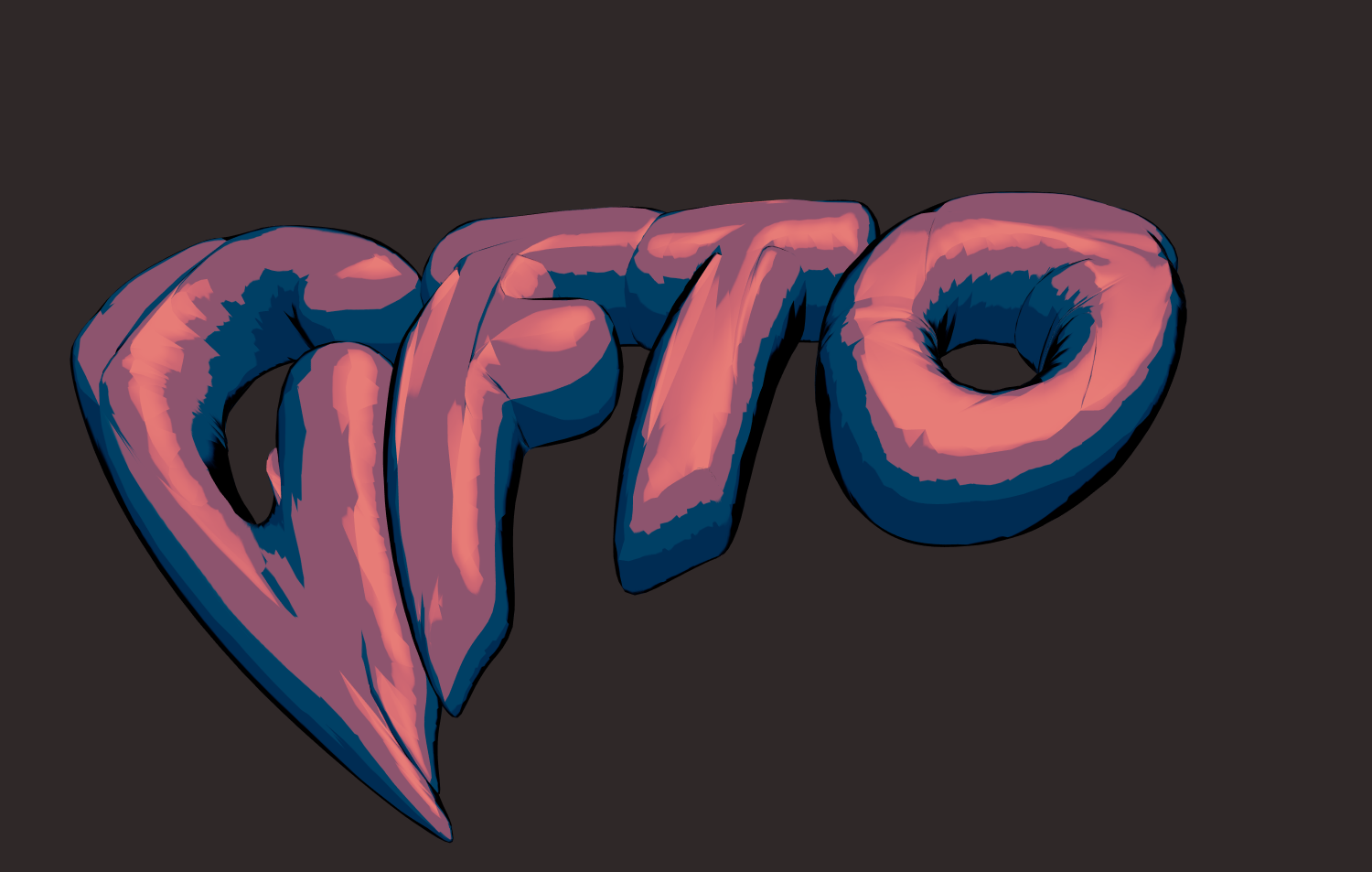
Мрачный и яркий стиль, чтобы сделать текст по-настоящему пугающим. Идеально для Хэллоуина и игр.
Сделайте надпись с реалистичным зеркальным отражением. Премиальный и технологичный вид.
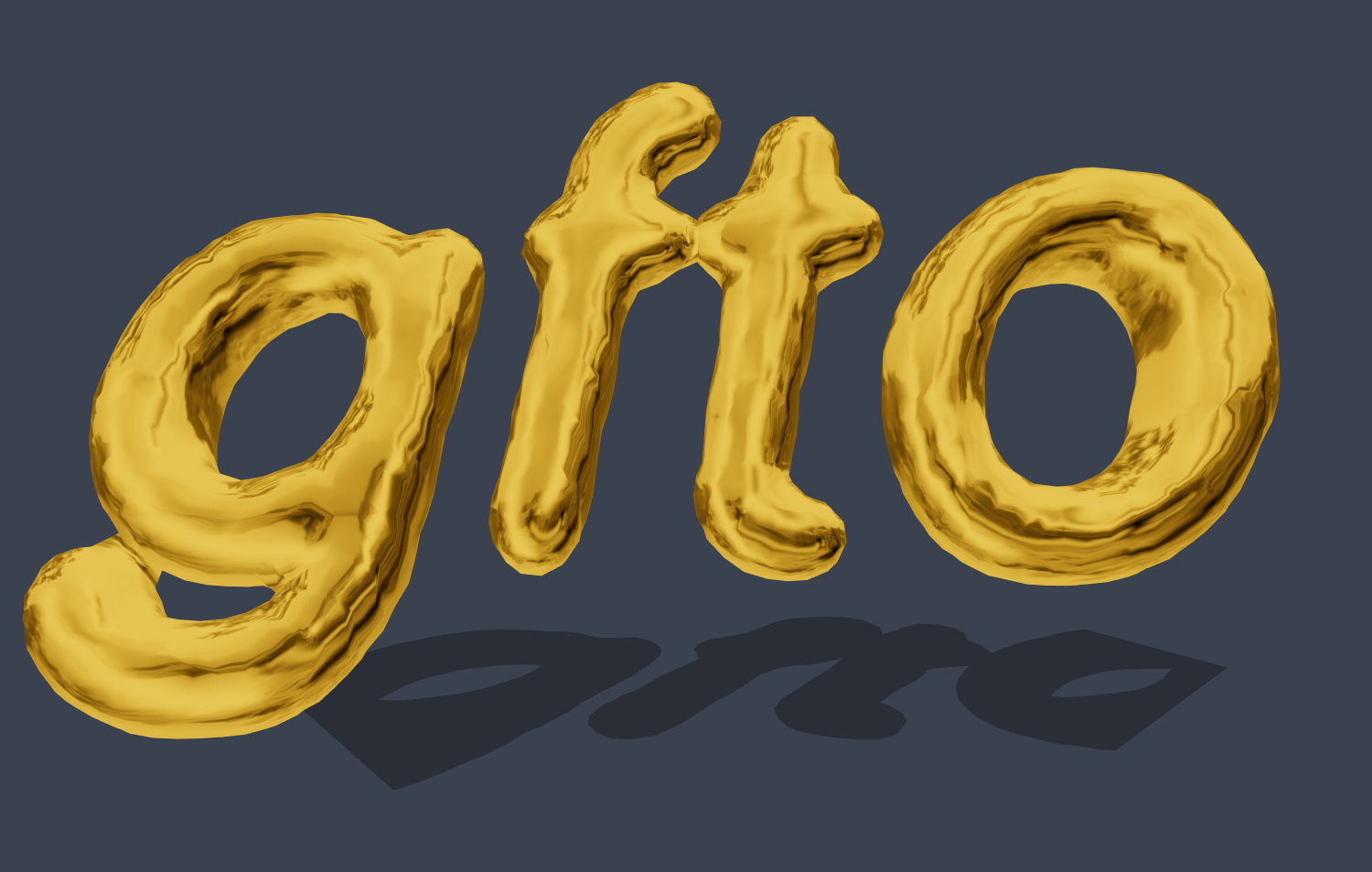
Объемные золотые буквы с глянцевой поверхностью для создания роскошной и красивой надписи.
3D эффект с органической формой. Плавные линии и реалистичная жидкая текстура для вашей надписи.
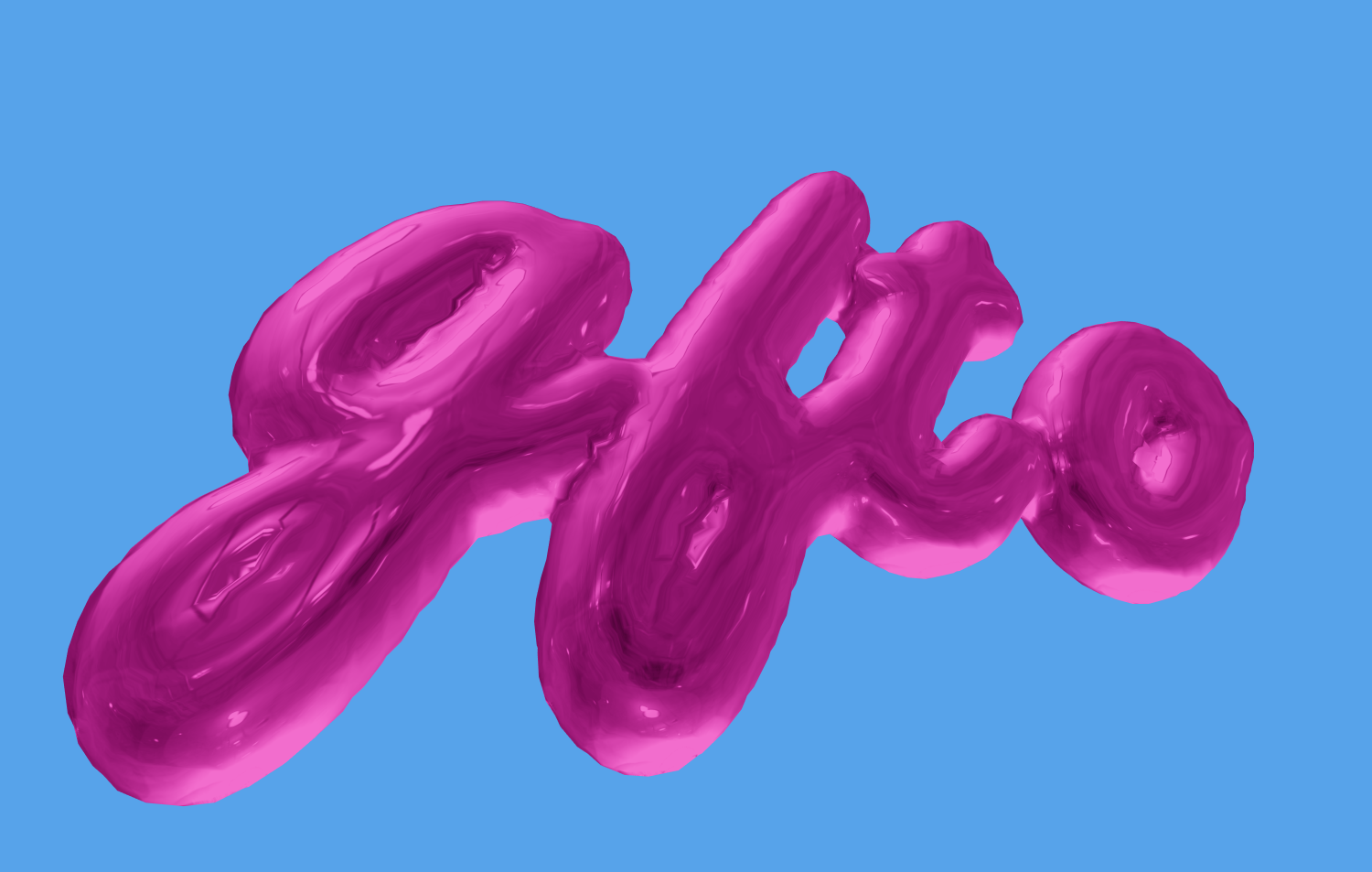
Легкий и воздушный стиль для праздничных красивых надписей и поздравлений.
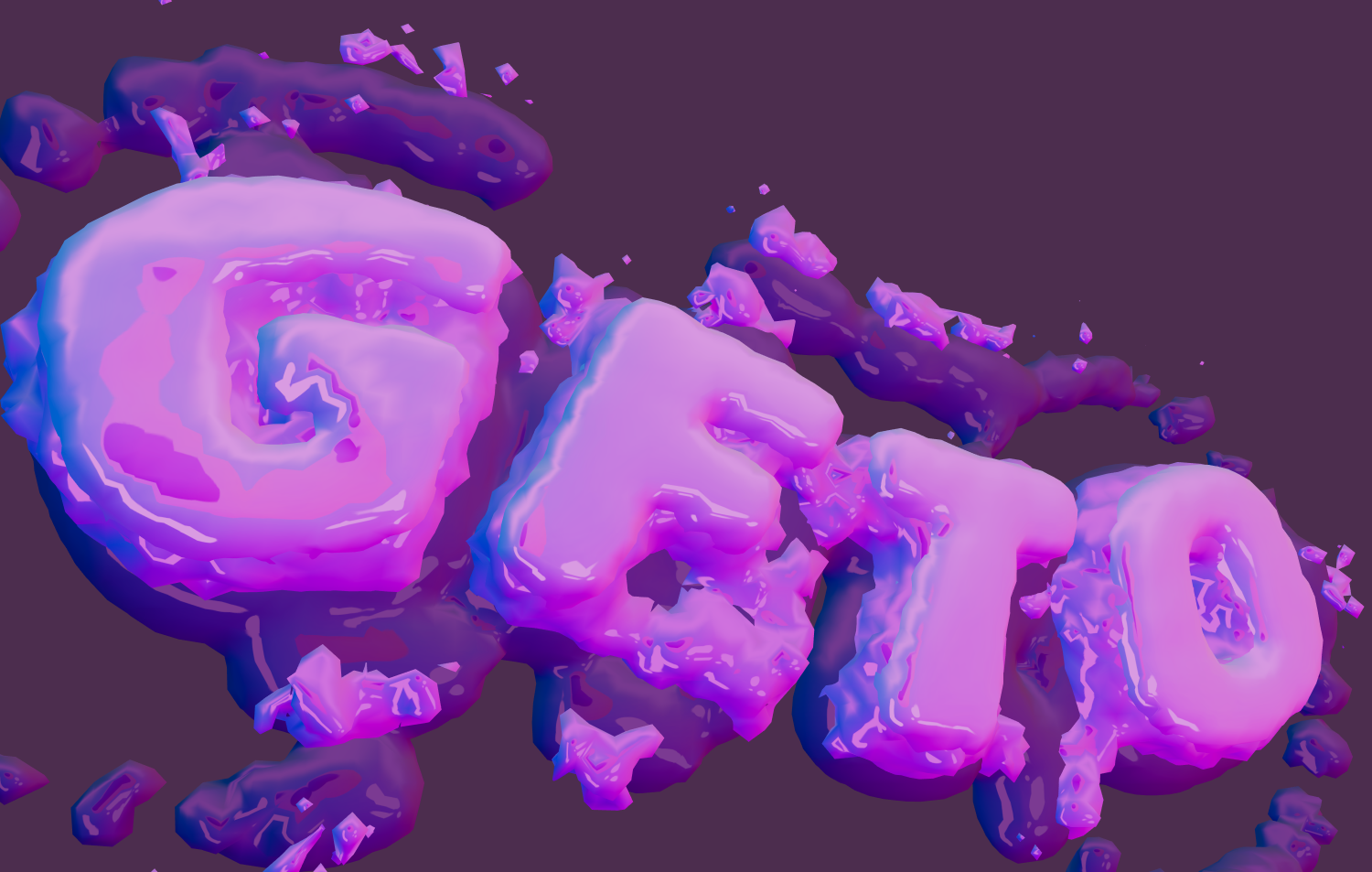
Напишите текст липким и глянцевым шрифтом с эффектом плавления. Очень креативно!
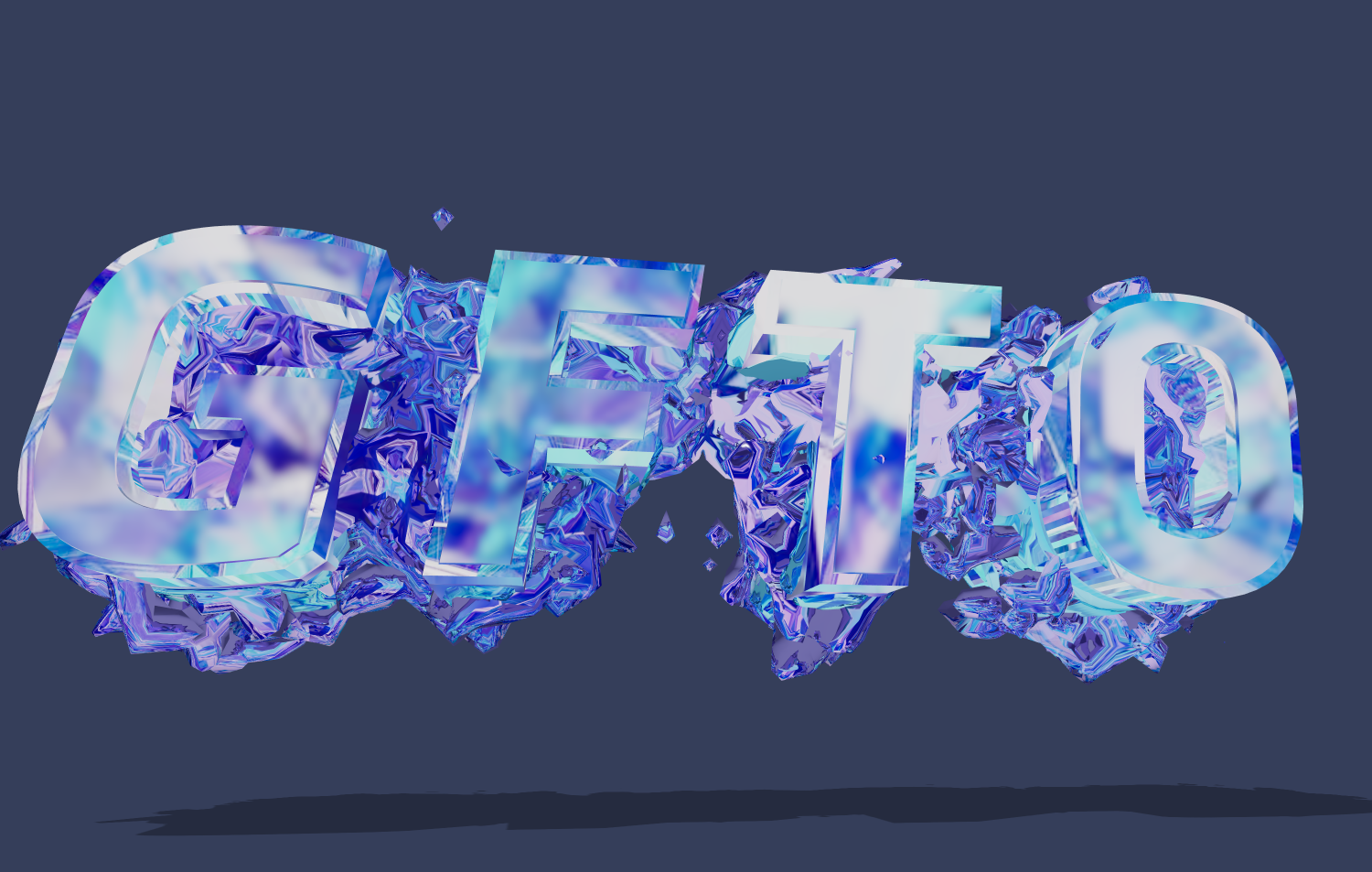
Создайте красивую надпись из стекла с эффектом трещин. Хрупкая элегантность с элементами брутальности.
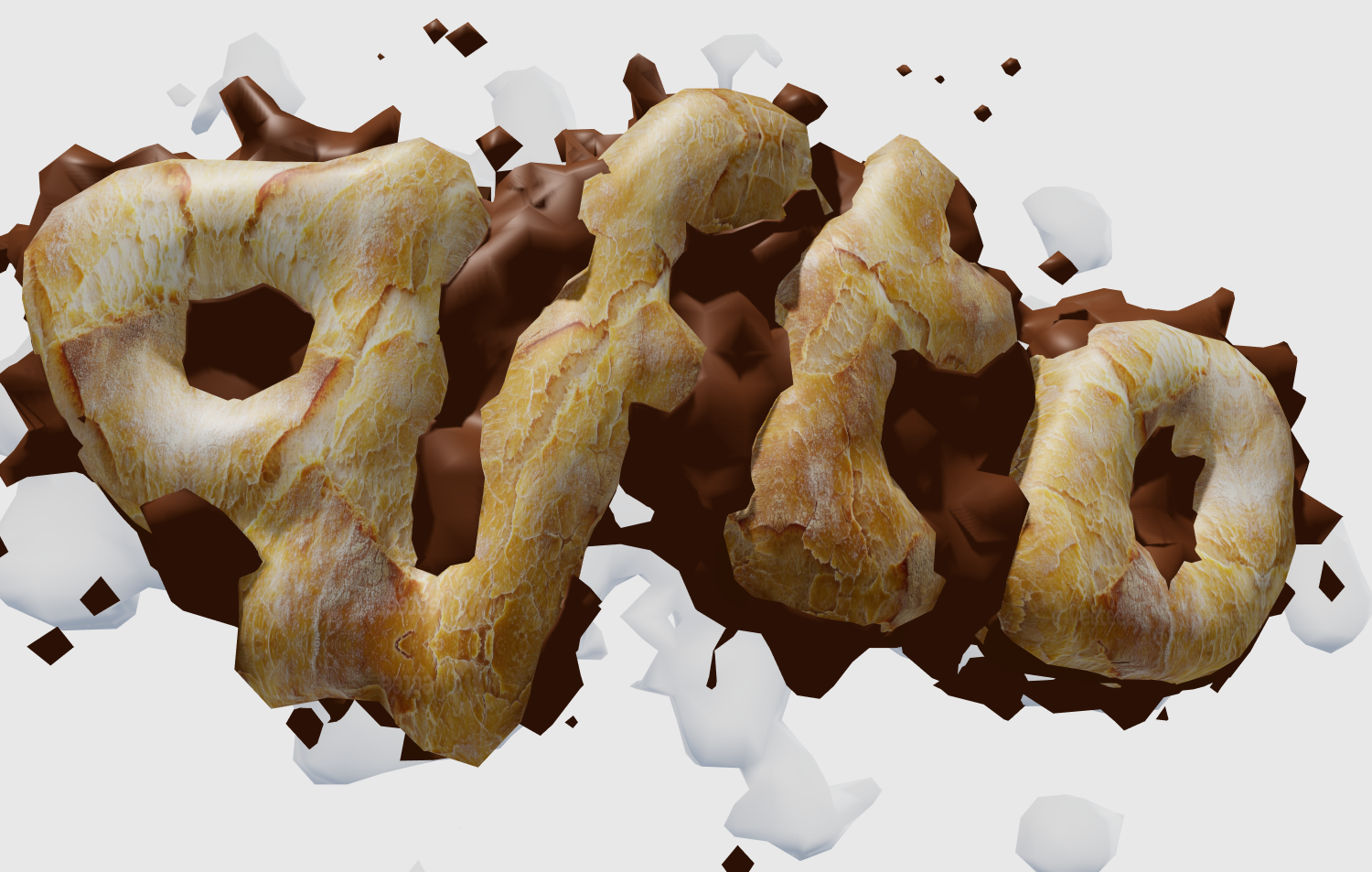
Аппетитный дизайн для красивых надписей в кондитерских и пекарнях. Текст из теста и шоколада.
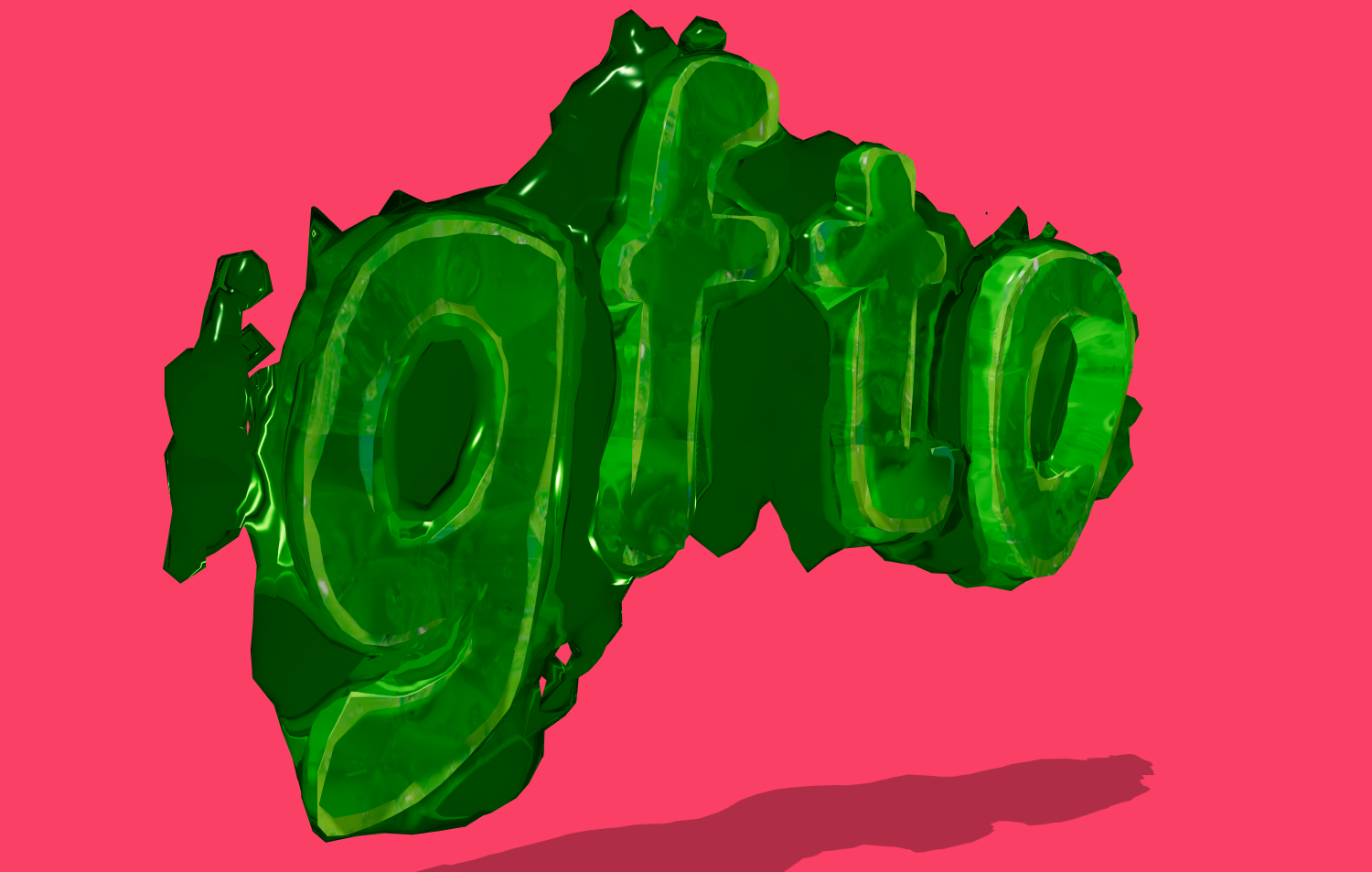
Создайте яркий зеленый текст с глянцевой текстурой слизи для забавной и необычной надписи.
Сделайте надпись с эффектом брызг и потеков крови. Идеально для хоррор-тематики и триллеров.
Эффект расплавленного металла, который растекается по поверхности из золотых осколков. Роскошный и красивый стиль.
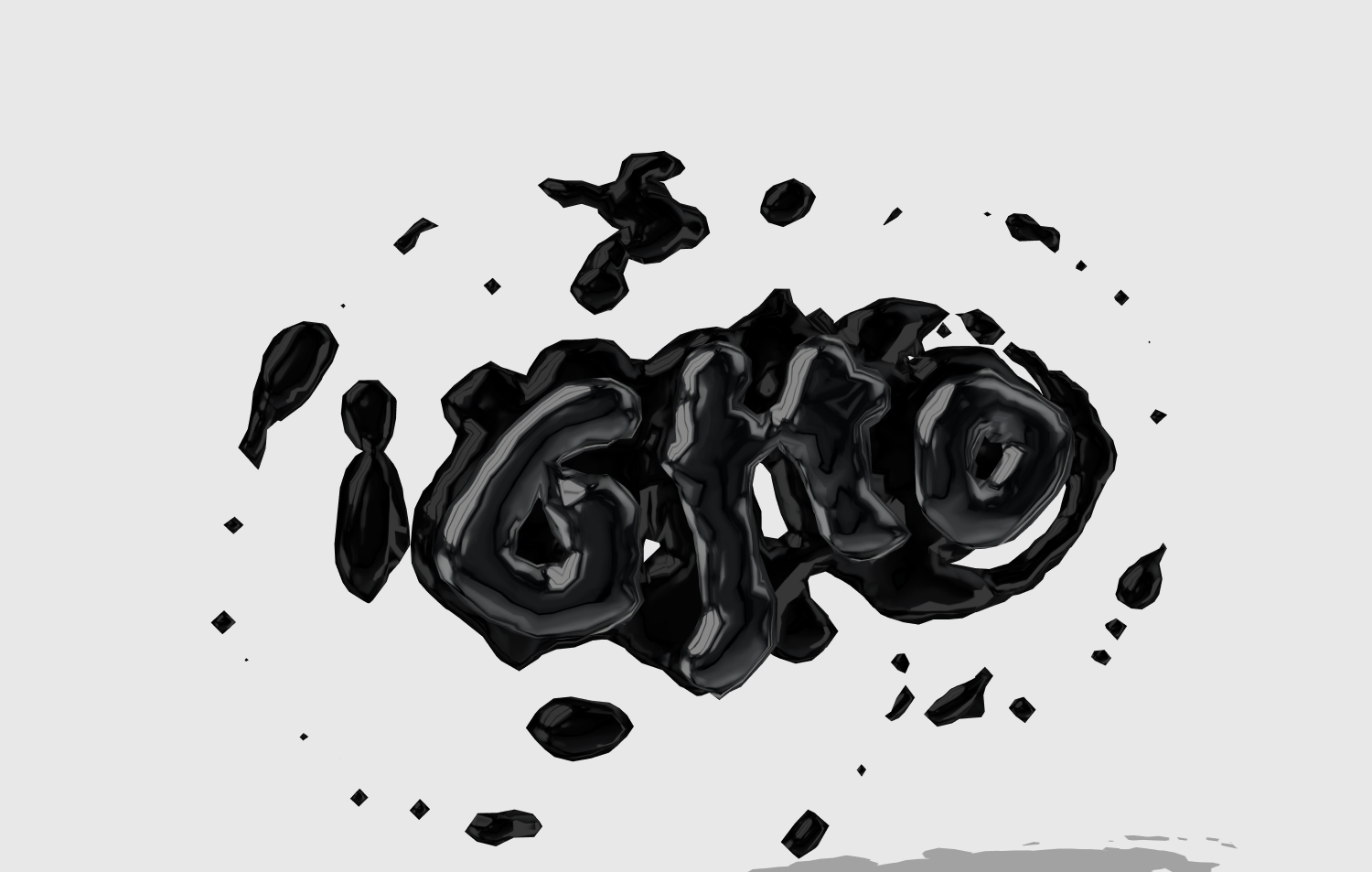
Текстовый эффект, имитирующий густую нефть или смолу с глянцевыми бликами и реалистичными брызгами.
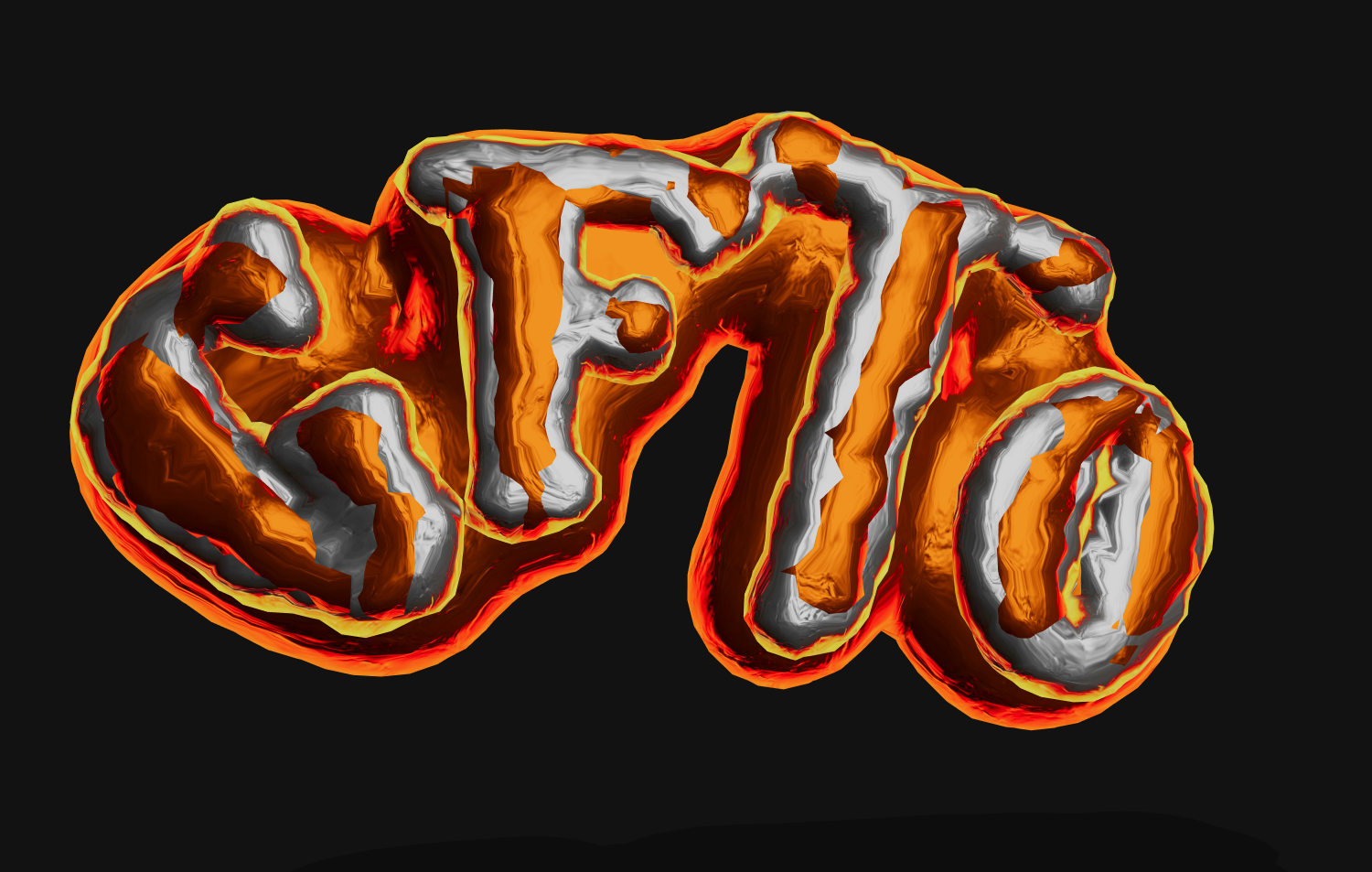
Огненный текстовый эффект кованого металла с трещинами. Мощь и сила в каждой букве вашей красивой надписи.
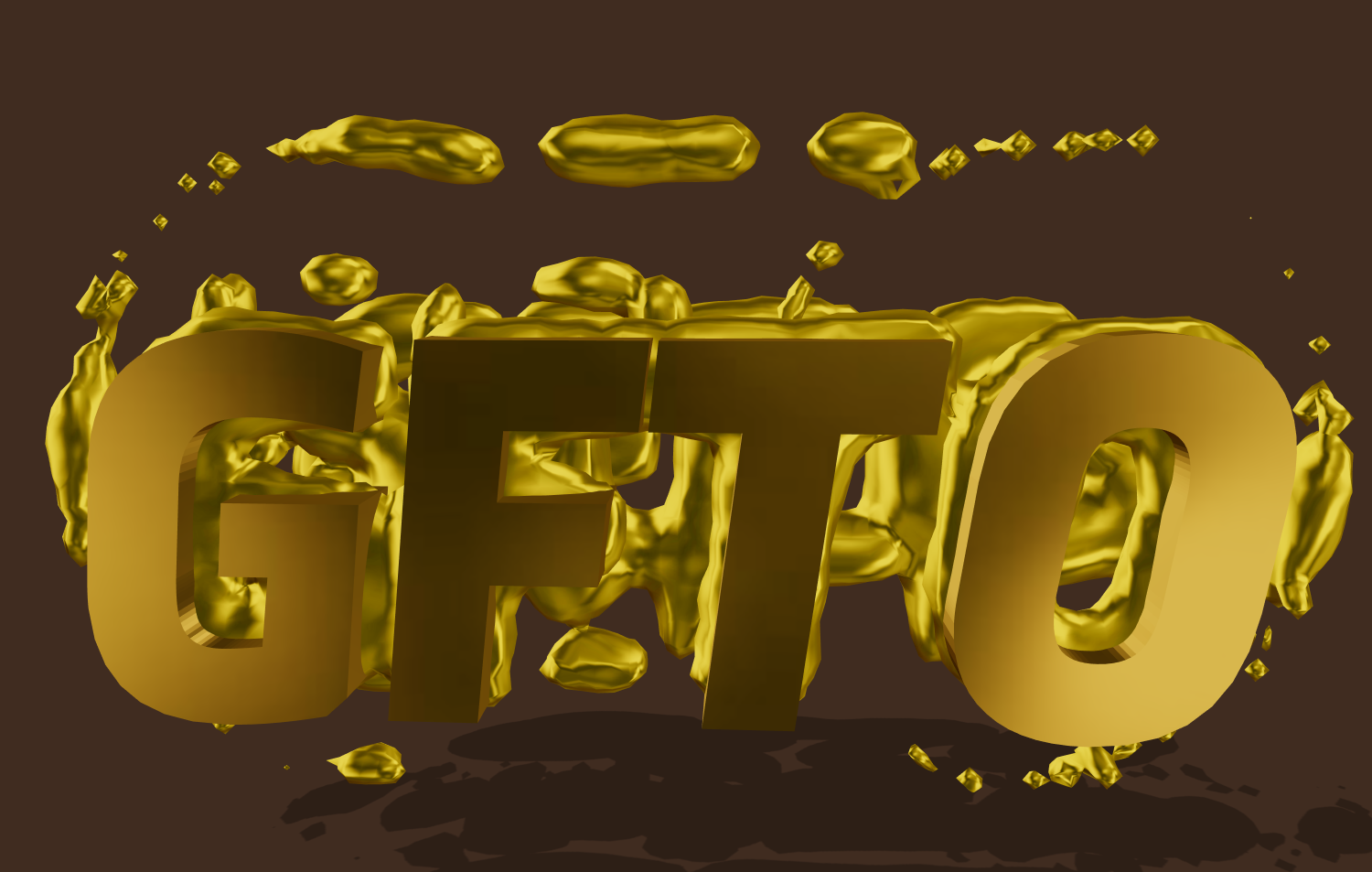
Создайте красивую надпись из расплавленного жидкого золота с динамичными брызгами.
Футуристичный текстовый эффект с ячеистой структурой. Отлично подходит для тем технологий и науки.
Объемный текстовый эффект пены и мыльных пузырей. Легкий, чистый и игривый красивый шрифт.
Современный 3D-эффект жидкого хрома или ртути. Идеален для музыкальных обложек и брендинга в стиле Y2K.
Создайте красивую надпись с текстурой старой ржавчины. Отлично для стилей гранж и индастриал.
Стильный эффект надувных букв из золотой фольги. Объемный, глянцевый и привлекающий внимание.
Элегантный стеклянный текстовый эффект с реалистичным преломлением света для красивой надписи.
Динамичный и взрывной текстовый эффект, будто буквы разлетаются на мелкие острые осколки.
Агрессивный и стильный игровой текст для логотипов киберспортивных команд и стримеров.
Объемный и мягкий пластилиновый текст. Идеально подходит для детских проектов и творческих работ.
Яркий и аппетитный текстовый эффект в виде фруктовых конфет. Создает позитивное настроение.
Объемные буквы с фиолетовым градиентом на фоне космоса. Для космических и фэнтезийных тем.
Легкий и воздушный текст с мягким контуром. Создает ощущение легкости и мечтательности.
Классический объемный текст в игровом стиле с яркими цветами для вашей красивой надписи.
Яркий и динамичный игровой текстовый эффект в стиле граффити с глянцем и глубокой тенью.
Классический ретро текстовый эффект с характерным градиентом и стилистикой синтвейва.
Забавный мультяшный текст с эффектом тающей краски или цветной слизи. Идеально для анимации.
Яркий и динамичный мультяшный пузырчатый шрифт. Отлично подходит для комиксов и игровых заголовков.
Мощная хромированная надпись с эффектом многослойной стали. Для брутального и технологичного дизайна.
Объемный хромированный текстовый эффект в стиле металла. Универсальный и стильный красивый шрифт.
Роскошный золотой глянцевый стиль для шрифта. Подчеркните премиальность вашего бренда красивой надписью.
Массивный эффект текста, имитирующий литой золотой слиток. Символ надежности и богатства.
Объемный кристаллический текст с глянцевым покрытием и огненным градиентом внутри.
Трендoвый объемный текстовый эффект в популярном стиле Y2K. Для модных и современных дизайнов.
Создайте объемный текст в стиле стикера или наклейки с четким белым контуром и тенью.
Мягкий и объемный шрифт в стиле надувного пластика или фольгированных шаров. Легкий и дружелюбный.